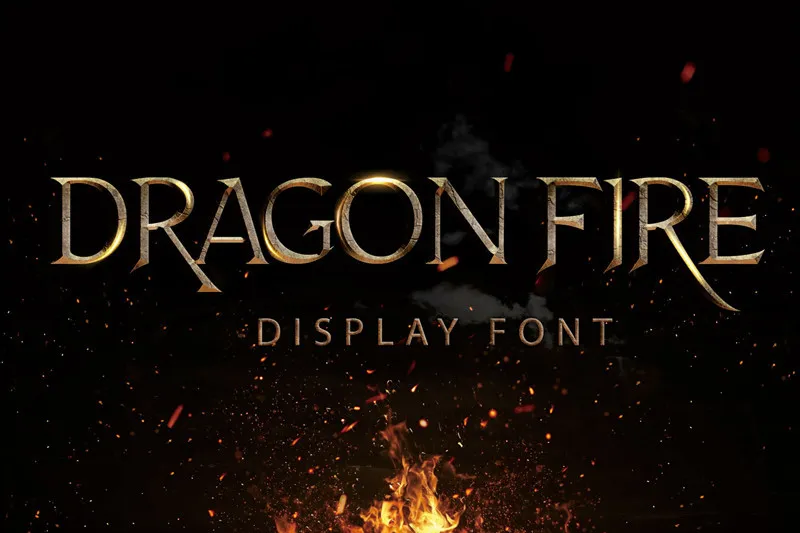
Dragon Fire Display Font – Download Grátis
Saudações, criamos Dragon Fire Font para vocês. Essa é uma fonte serif moderna com muitas alternativas, perfeita para uso em cabeçalhos e outras seções que precisam de um pouco mais de destaque na sua página. Com alternativas abundantes, você pode misturá-las para criar algo único a cada projeto. Dragon Fire é um excelente fonte para displays, que combina perfeitamente tanto em tamanhos grandes quanto menores. Foi projetado e compartilhado por inspiratype99. Esta elegante fonte é ideal para logotipos, posters, jogos e qualquer outro projeto criativo. Dragon Fire é uma fonte de exibição maravilhosa que traz vida à sua marca ou trabalho. Ela combina a modernidade da serif com um charme sofisticado que certamente dará o toque final ao seu projeto. Não perca esta oportunidade única para revolucionar suas apresentações e identidades visuais!